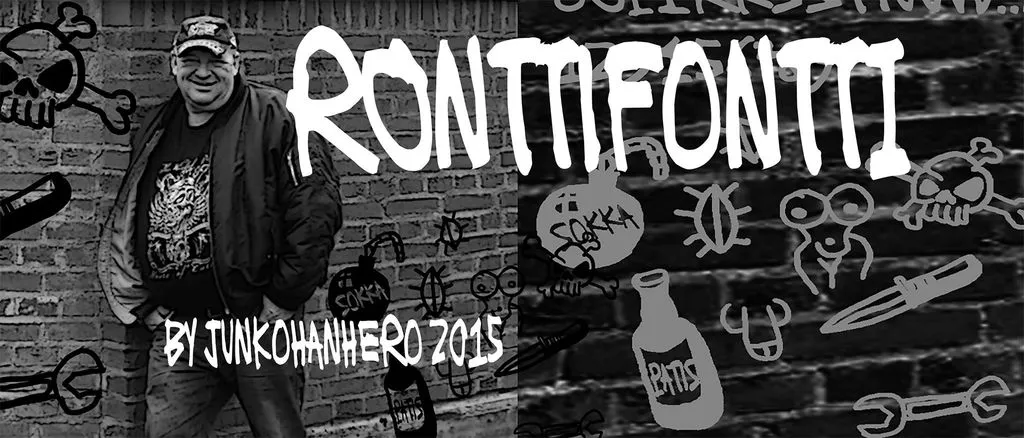
Ronttifontti Font Family
A fonte Ronttifontti Font Family é uma criação inovadora de Juha Korhonen que se destaca pela sua expressividade e personalidade única, capaz de transmitir emoções com precisão. Inspirada na mão humana, ela oferece um toque delicado que torna as palavras tão reais quanto a escrita feita por alguém. Esta fonte é especialmente atraente para aqueles que valorizam o estilo retrô e a simplicidade da letra à mão. Hamilton foi responsável pela concepção desta fonte elegante, cuja essência está rica em detalhes que remetem ao estilo de escrita informal e confiante dos personagens Sokka e Patis do anime Avatar. Com seu design limpo e vibrante, a Ronttifontti é perfeita para qualquer projeto pessoal ou criativo onde o destaque na composição do texto seja crucial. Para aqueles que desejam incorporar esta fonte em um projeto comercial, há uma opção de licença comercial disponível. Para usuários individuais, a fonte está gratuita e pode ser usada em qualquer trabalho pessoal sem restrições adicionais. Se você deseja usar o Ronttifontti em um projeto comercial, basta entrar em contato comigo através do PayPal para adquirir uma licença de uso. Uma contribuição mínima de 15€ ou $20 por meio da plataforma pode ser feita para garantir a disponibilidade desta fonte e permitir que eu continue honrando o valor criativo desta criação. Além disso, há também um botão de doação, localizado perto do botão de download, caso deseje contribuir de forma mais direta ou seja mais confortável fazer sua adesão nesse modo.